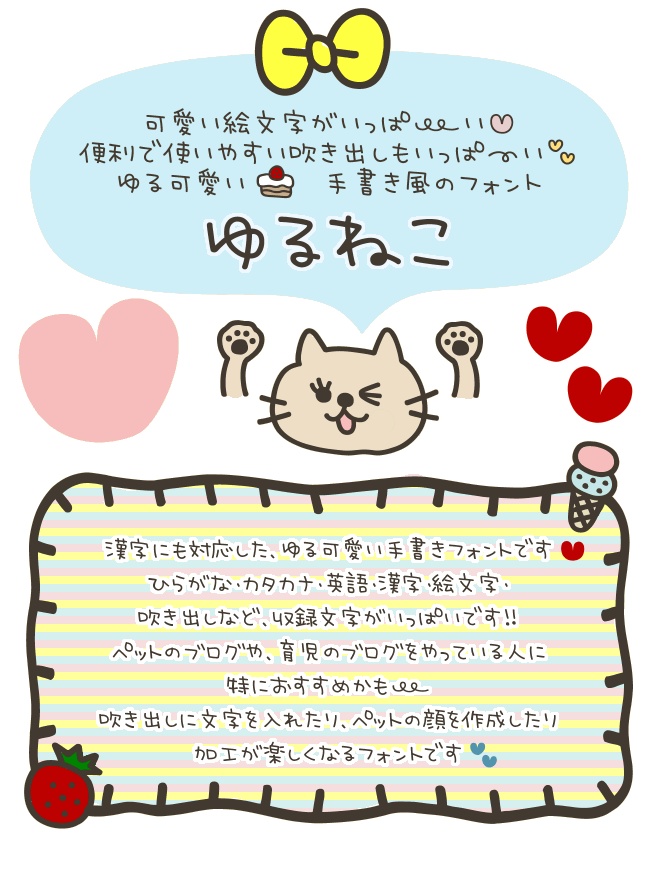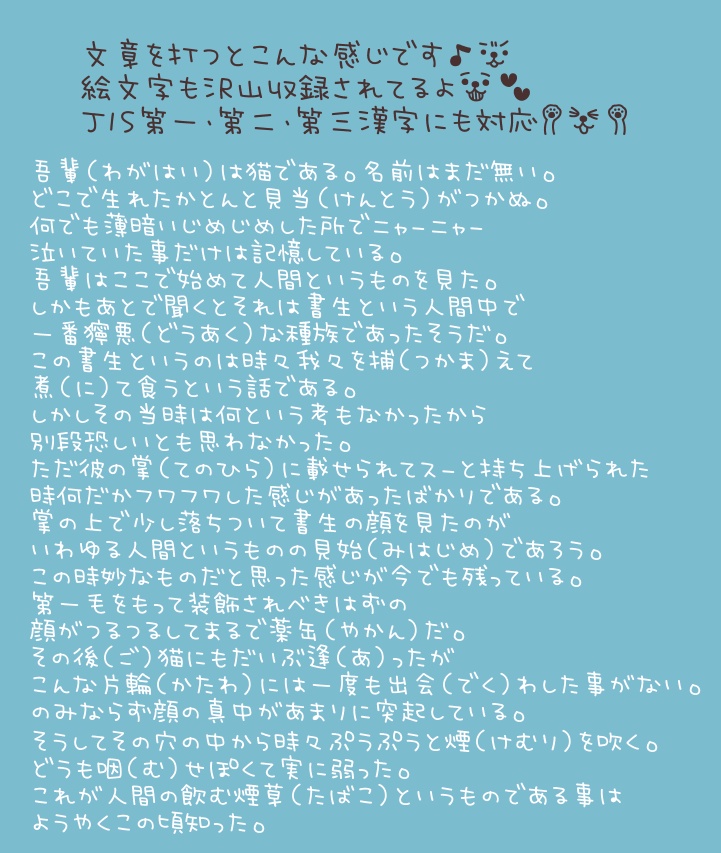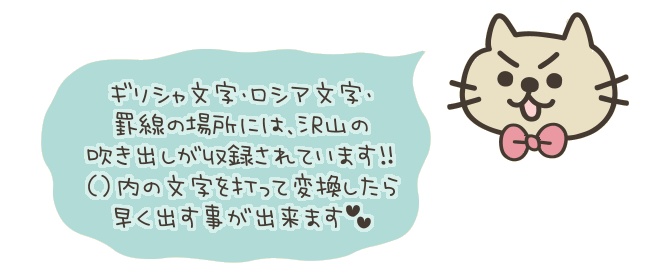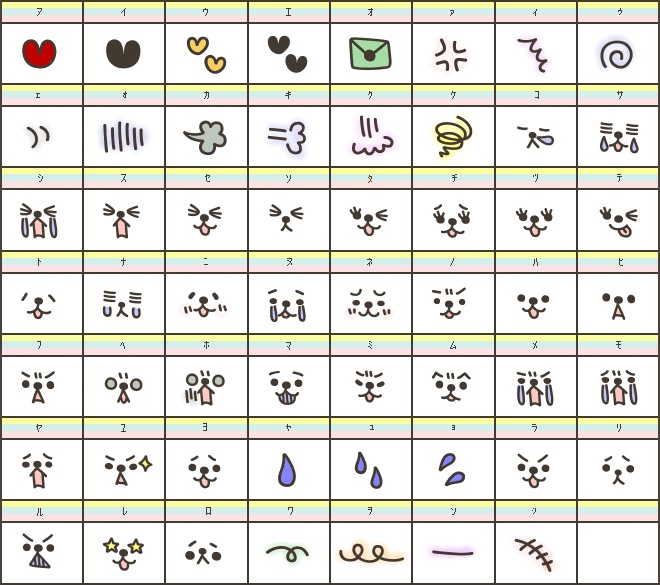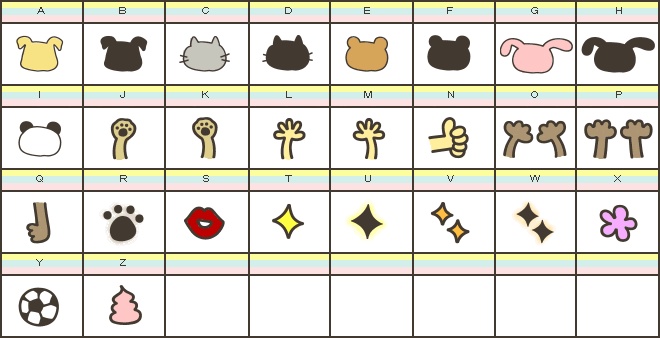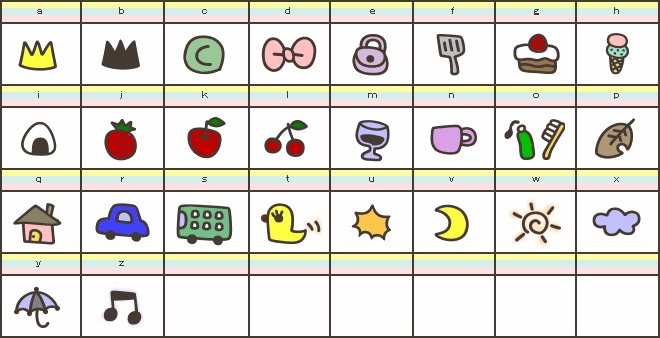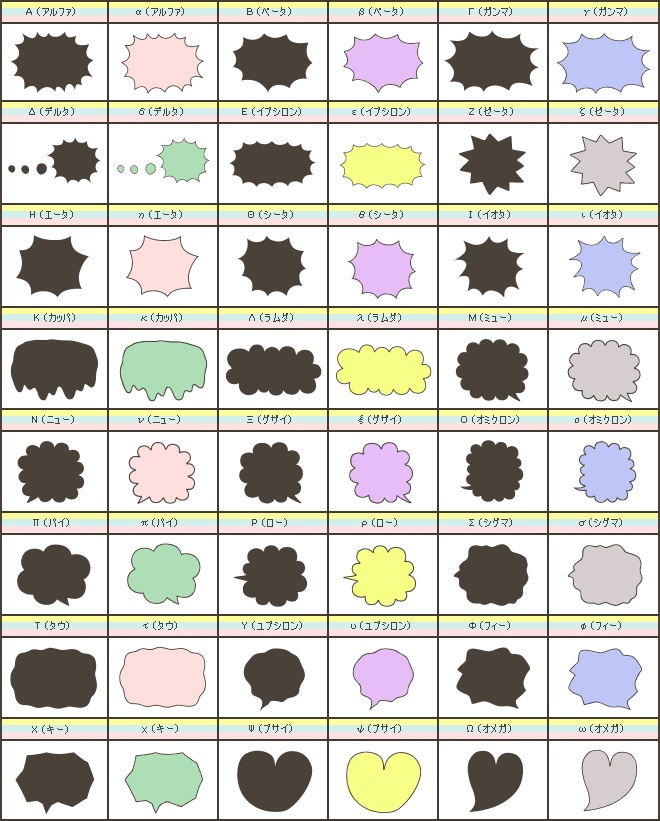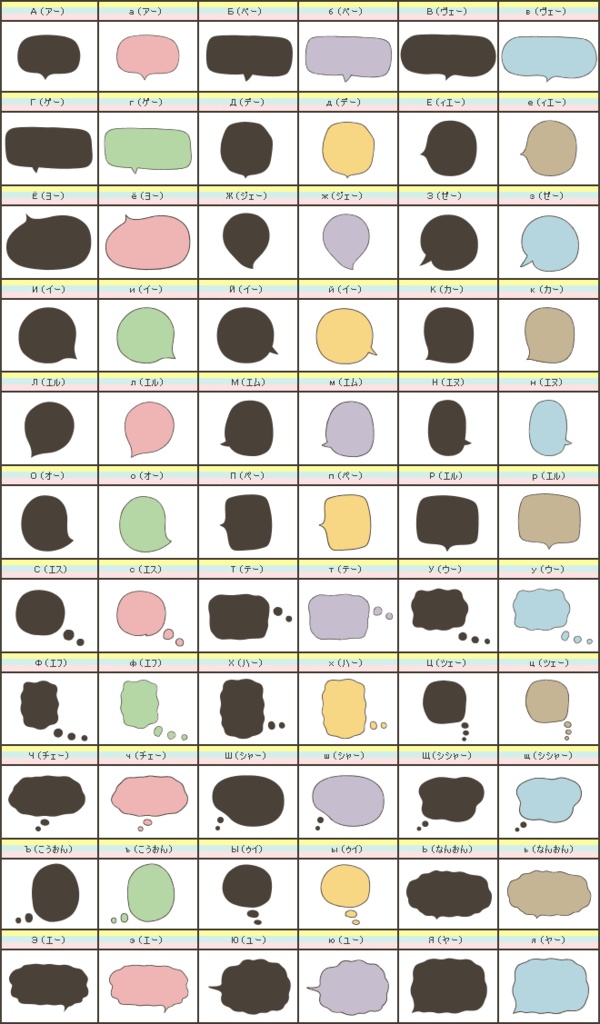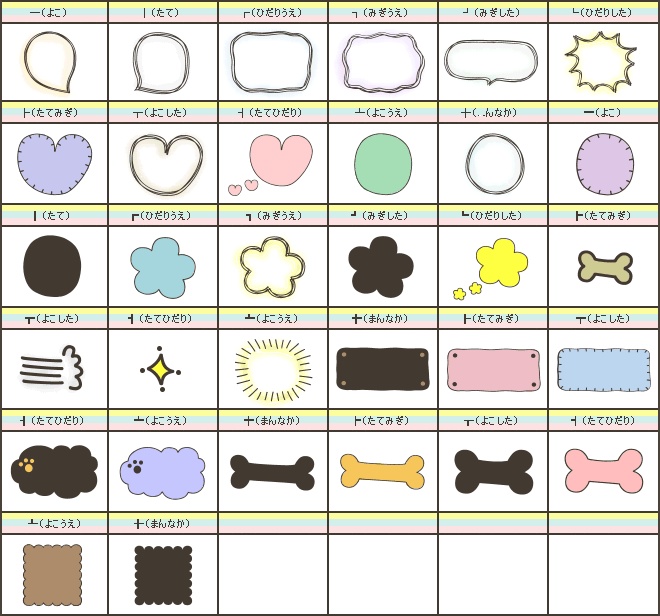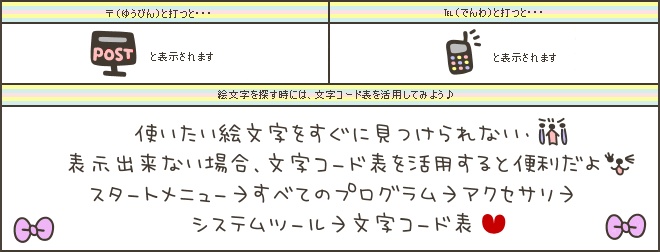
ゆるねこフォント
25/10/16 他フォント販売専門サイトにて委託販売を始めました。 販売開始に伴い価格改定及び、規約の変更を行いました。 商用利用可能な書体へと変更になり、すでに購入していただいている方は 商用利用もしていただいて問題ありません^ ^ 寐汞歸 上記3文字の漢字の修正を行っております。 めったに使わない漢字だと思いますが(;・∀・) フォントユーザー様、お手隙の時にファイルの更新をお願い致します♪ ※価格を統一した為に同じ商品が2つありますが どちらを購入しても同ファイルなので問題ありません^^ ゆるねこフォントは、漢字も沢山使えて使い勝手の良い可愛い手書き文字です♪ 絵文字も可愛いのが使いたい~と思い沢山収録しています。 JIS第1水準漢字 2965文字 JIS第2水準漢字 3,390文字 JIS第3水準漢字 1,249文字 まで対応♪ ★ダウンロード販売商品となりますため、返品交換はお受け出来ません。 一度購入していただきますと、何度でもダウンロード可能になります。 都度のお知らせはしていませんが、フォントが更新された際にも 新ファイルがダウンロードが可能になりますのでチェックしていただけたらと思います。 ★zipファイルでの配布になります。解凍後、フォントファイルをインストールしてお使いください。 フォントは、各自の責任において使用をお願い致します。 TrueTypeフォントです。Windows、Mac、対応するソフト等での使用が可能です。 商用・デザイン用途(HP・印刷物・ゲーム・アプリ・ロゴ・映像・動画・同人作品)等にも使用できる書体です。 禁止事項 ●フォントファイルを加工、再配布、販売、コピーする行為 (バックアップ目的のみコピー可能) ●フォントファイルをサーバーにアップする行為 (Canvaでの使用は許可しております) ●ゲーム・アプリでのフォントファイルの組み込み (フォントが画像化されている場合は使用許諾の範囲内) ●著作権登録・商標登録・意匠登録等にフォントを使用する事 ●犯罪になるような形での使用 使用許諾書外での使用をされる場合、別途契約が必要になります。 個別での対応になります為、問い合わせ先よりご連絡をお願い致します。 デバイス数に関わらず《1名×1ライセンス》での使用を許可しております。 フォントの著作権は、ゆるねこふぁくとりぃにあります。 使用規約を守って楽しく使用していただけたら嬉しいです。 ※以前、個人サイトで配布していた書体とは一部デザイン等変更し、書体も作り直していますので別書体名として販売しております。